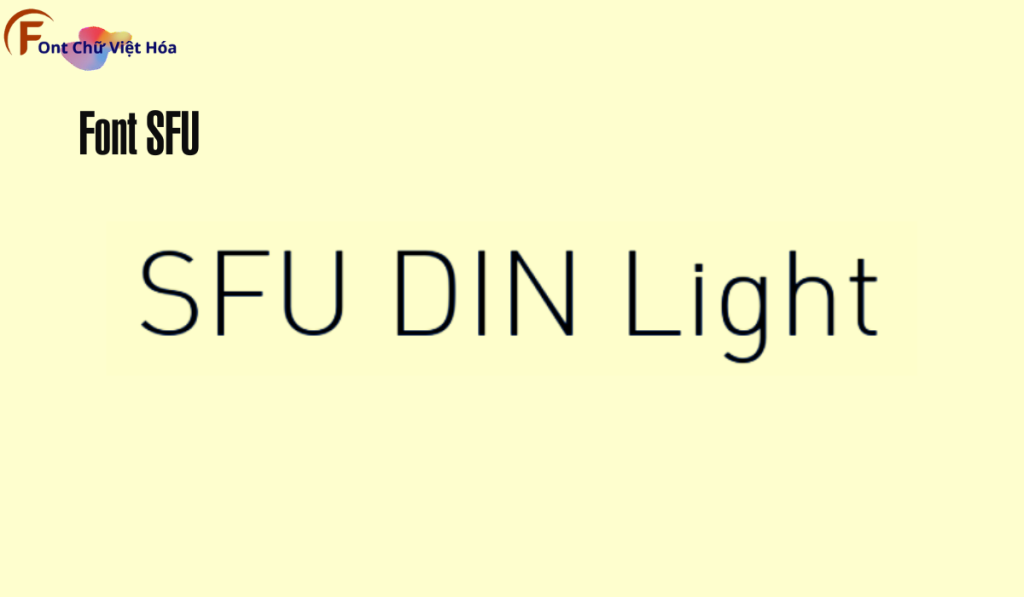
Tác giả: SFU
Bộ Font: SFU
Phân loại: Hiện đại, đơn giản
Kiểu chữ: Sans-serif
Độ dày: Light
Font SFU-Light Việt Hóa, thuộc bộ font SFU, mang phong cách sans-serif hiện đại với các đường nét thanh thoát và tinh tế. Font này được thiết kế nhằm mục tiêu tạo ra sự rõ ràng và dễ đọc, đặc biệt phù hợp cho các thiết kế như poster, logo, và tiêu đề. Đặc điểm hình dạng của SFU-Light là các đường nét nhẹ nhàng và tỷ lệ chữ cân đối, giúp tối ưu hóa không gian và tạo ấn tượng thị giác mạnh mẽ. Font này cũng đã được Việt hóa, mang đến sự linh hoạt và tiện dụng cho các dự án thiết kế bằng tiếng Việt, giúp người dùng dễ dàng tiếp cận và sử dụng.